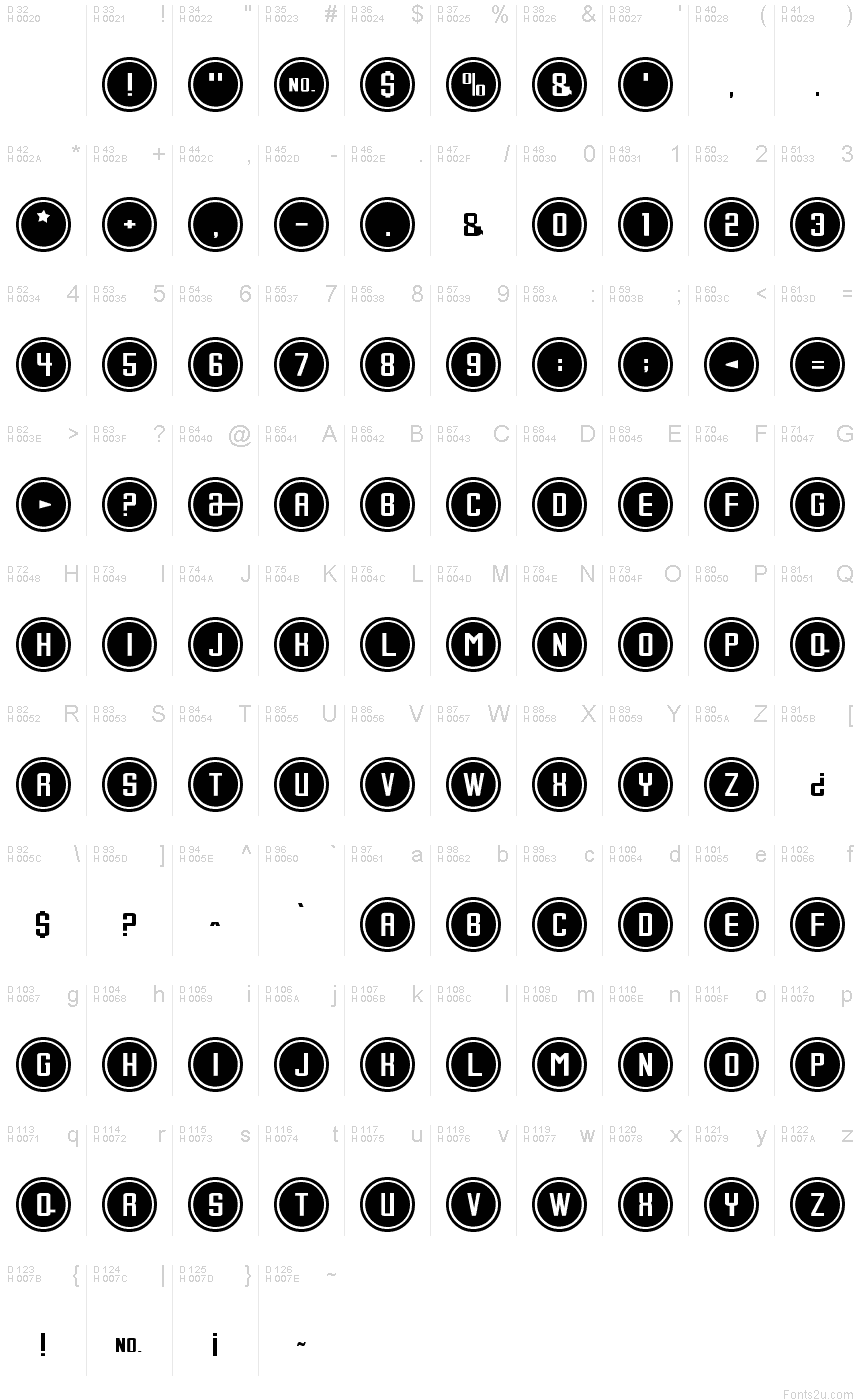
يعتبر خط Console Input خطاً زخرفياً مجانياً للعناوين من عائلة Console. يستقر كل حرف داخل دائرة سوداء جريئة ذات إطار مزدوج بارز، مما يذكرنا بصف من أزرار ألعاب الآركيد التي تنتظر الضغط عليها. تتميز الحروف بطولها وشكلها المربع بلمسة هندسية ومستقبلية، مما يضفي على العناوين طاقة «Push-to-start» قوية وتكاد تكون ملموسة، تجعلها تقفز من الشاشة.
باستخدام Console Input، يمكنك منح قنوات الألعاب، وفرق الرياضات الإلكترونية، وملصقات الـ retro-tech، وتذاكر الفعاليات، والشارات، وأزرار التنقل البارزة، ذلك الطابع القوي الشبيه بأجهزة الألعاب. يعمل هذا الخط المجاني بشكل أفضل عند استخدامه بأحجام كبيرة حيث يمكن للرموز الدائرية أن تتنفس؛ قم بإقرانه بخط بسيط وغير مزعج بلا زوائد (sans serif) للنصوص الثانوية، لتبقى الحروف ذات الطابع الأيقوني في دائرة الضوء.